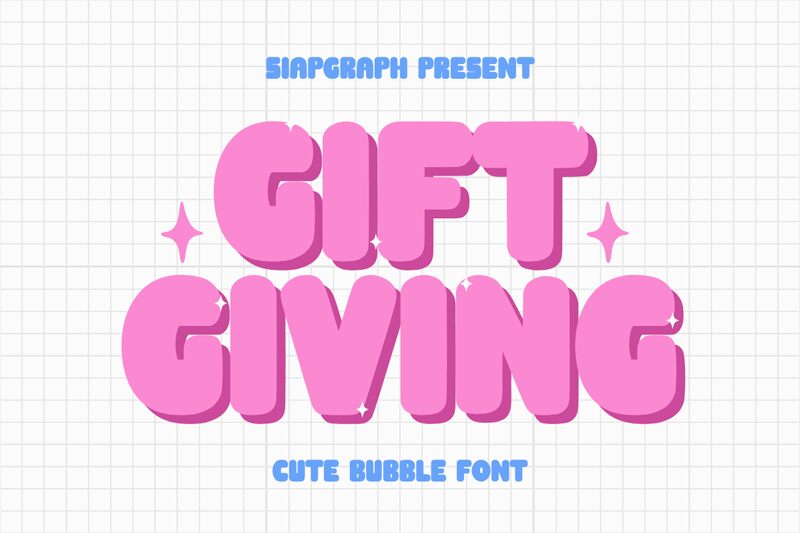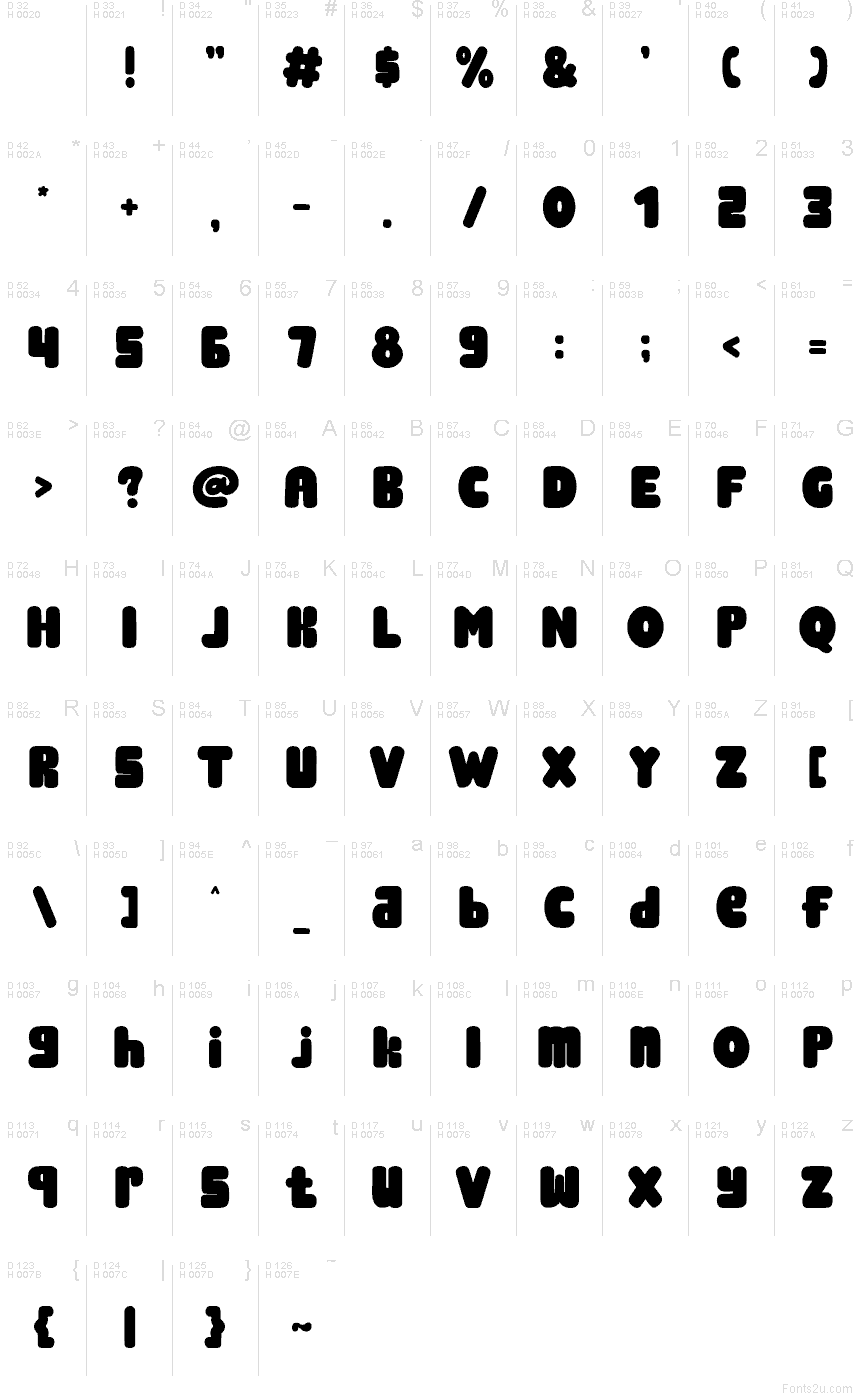
Gift Giving von SIAPGRAPH STUDIO ist eine kostenlose, groovige Display-Schrift, die durch ihre großen, abgerundeten Formen und tiefen Einschnitte besticht – das verleiht den Buchstaben eine weiche, fast aufgeblähte Silhouette. Dieser verspielte Rhythmus sorgt für eine freundliche, grafische Wirkung statt eines sterilen Looks und bietet genug Masse, damit auch kurze Wörter wie plakative Schriftzüge wirken.
Die Schrift eignet sich hervorragend für Einladungen, Geschenkanhänger, Kinderposter, Verpackungen und Social-Media-Grafiken, bei denen eine fröhliche Überschrift eine warme, weiche Ausstrahlung braucht. Die großzügigen Rundungen und der kompakte Rhythmus setzen zudem starke Akzente bei Sticker-Designs oder Branding-Projekten für Concept Stores, ganz ohne zusätzlichen Schnickschnack.